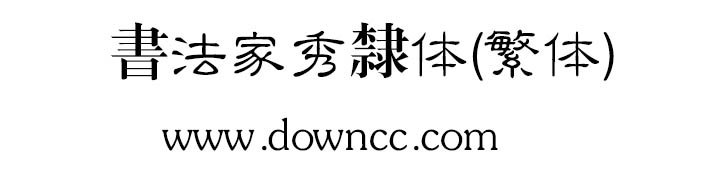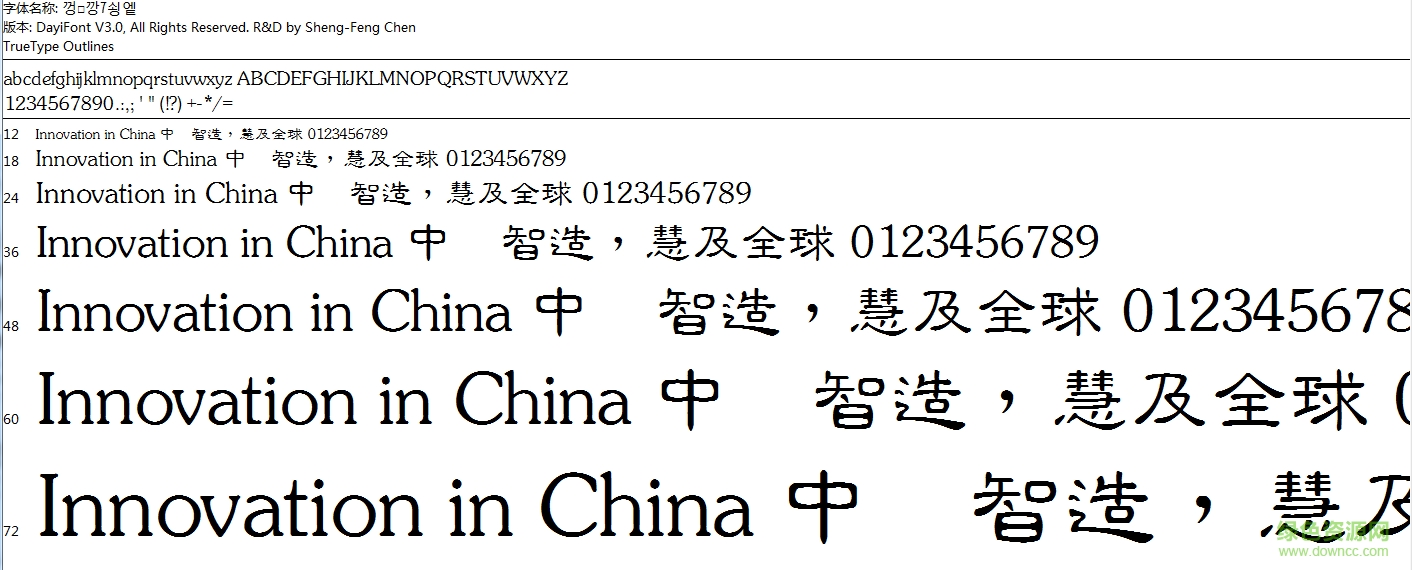
書法家秀隸體是一款極具藝術(shù)風(fēng)格的優(yōu)美字體。它是漢字書法中常見的一種字體。其字形較為正方,不像隸書寫成扁形。喜歡的朋友可以來綠色資源網(wǎng)下載試試哦!
①結(jié)體改篆書的形象化而為點劃符號化;
②字形改篆書的圓長而為方扁;
③筆劃有折無轉(zhuǎn),并有波挑。方筆和圓筆兼用。